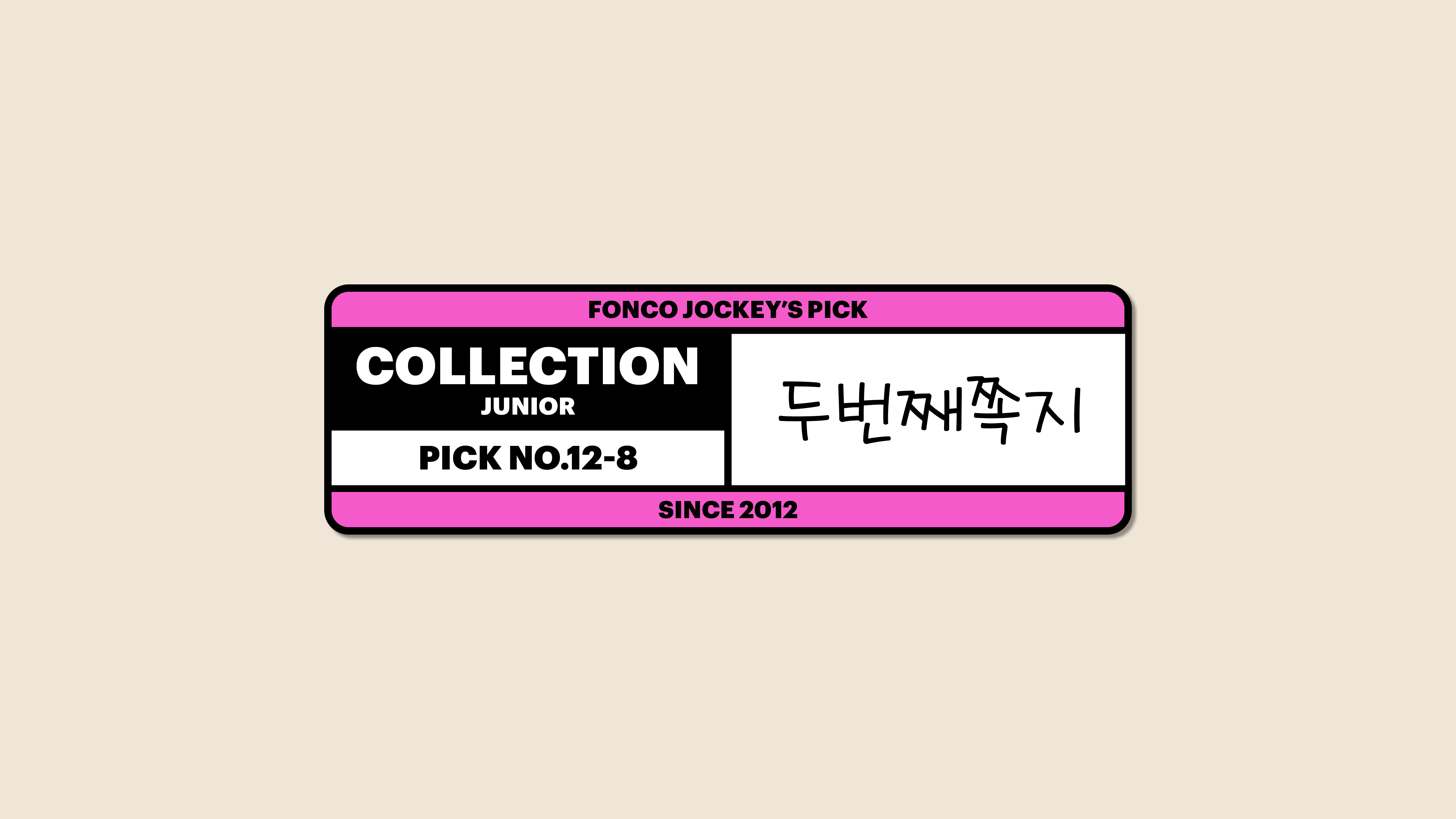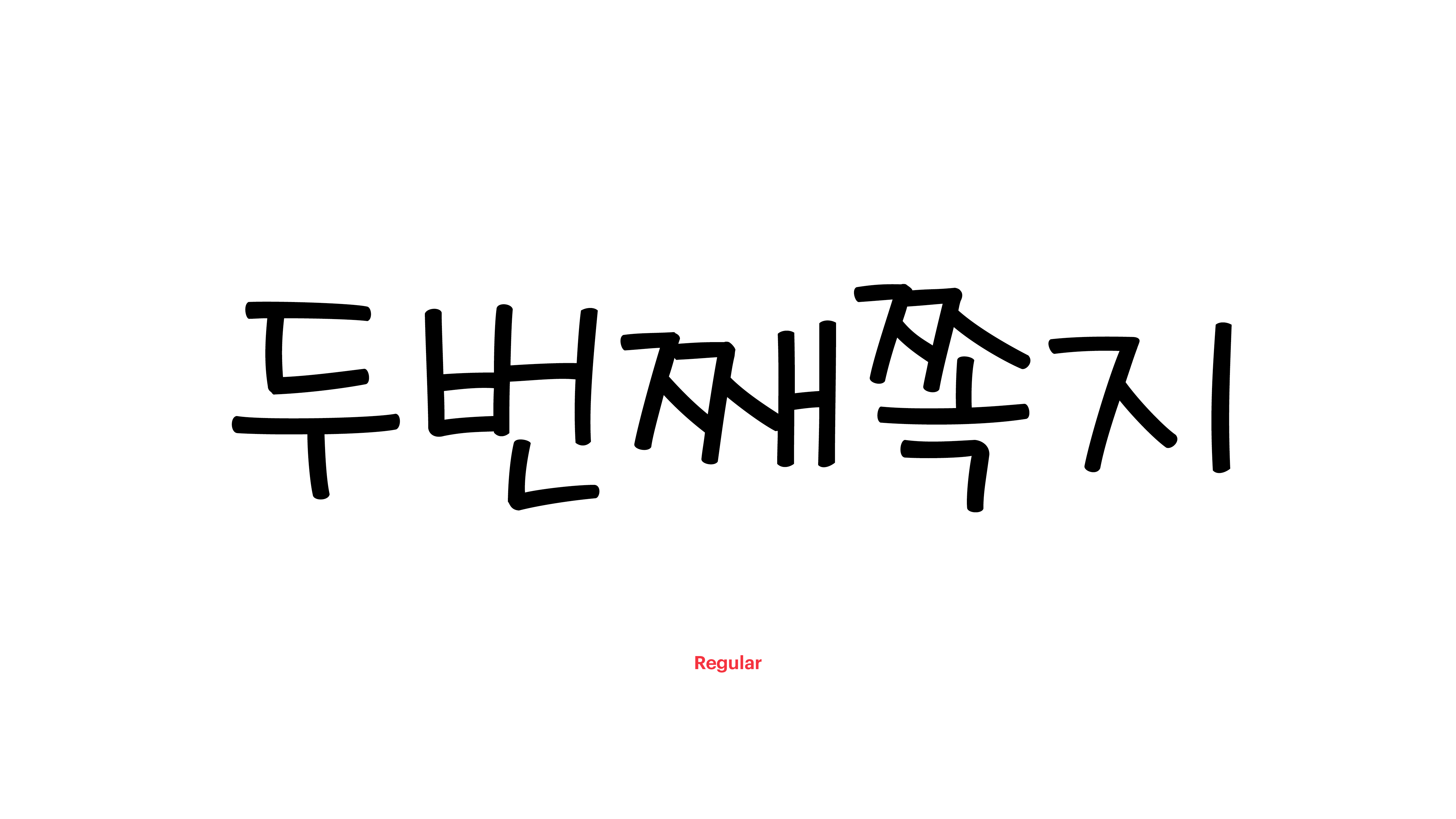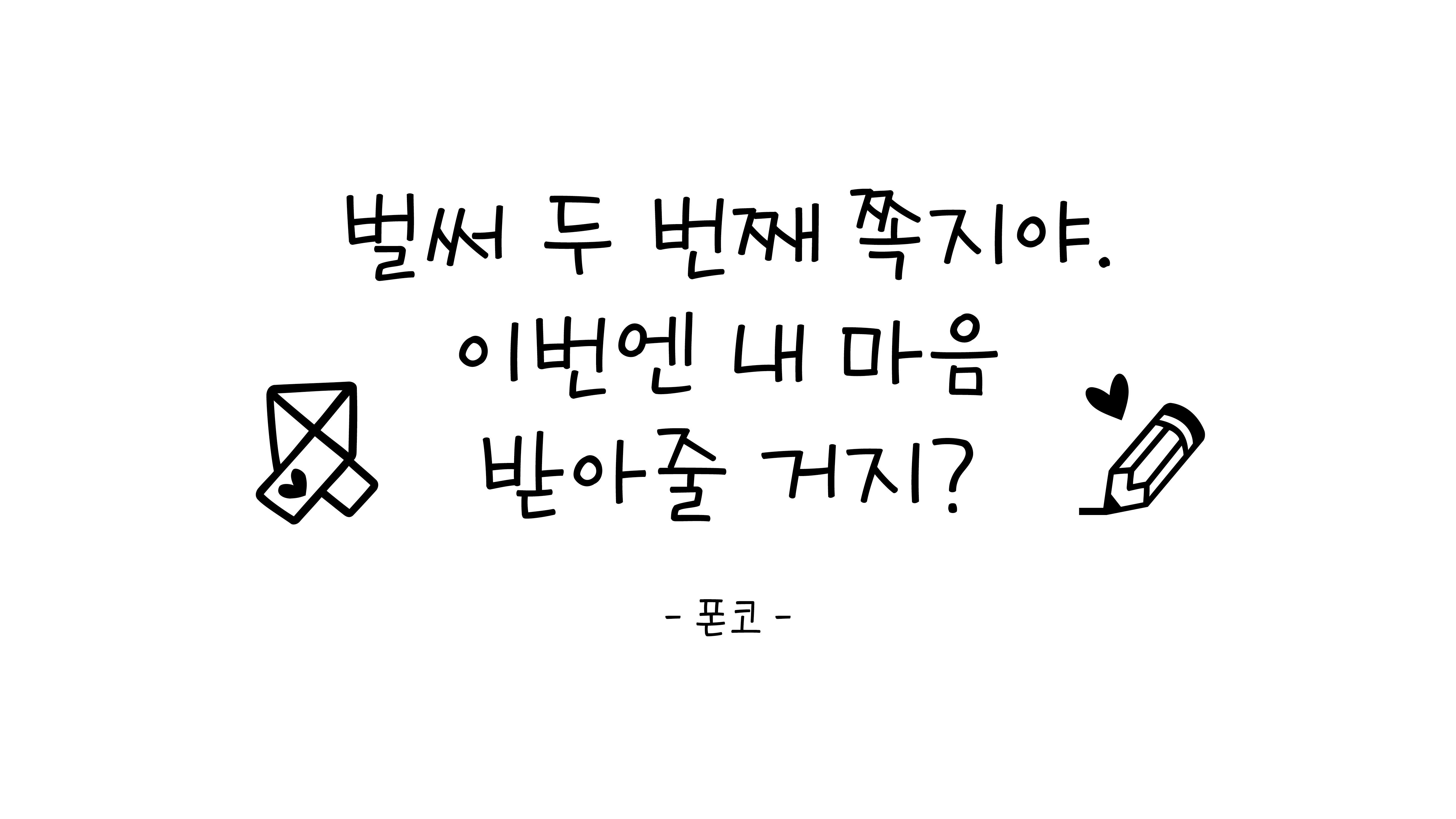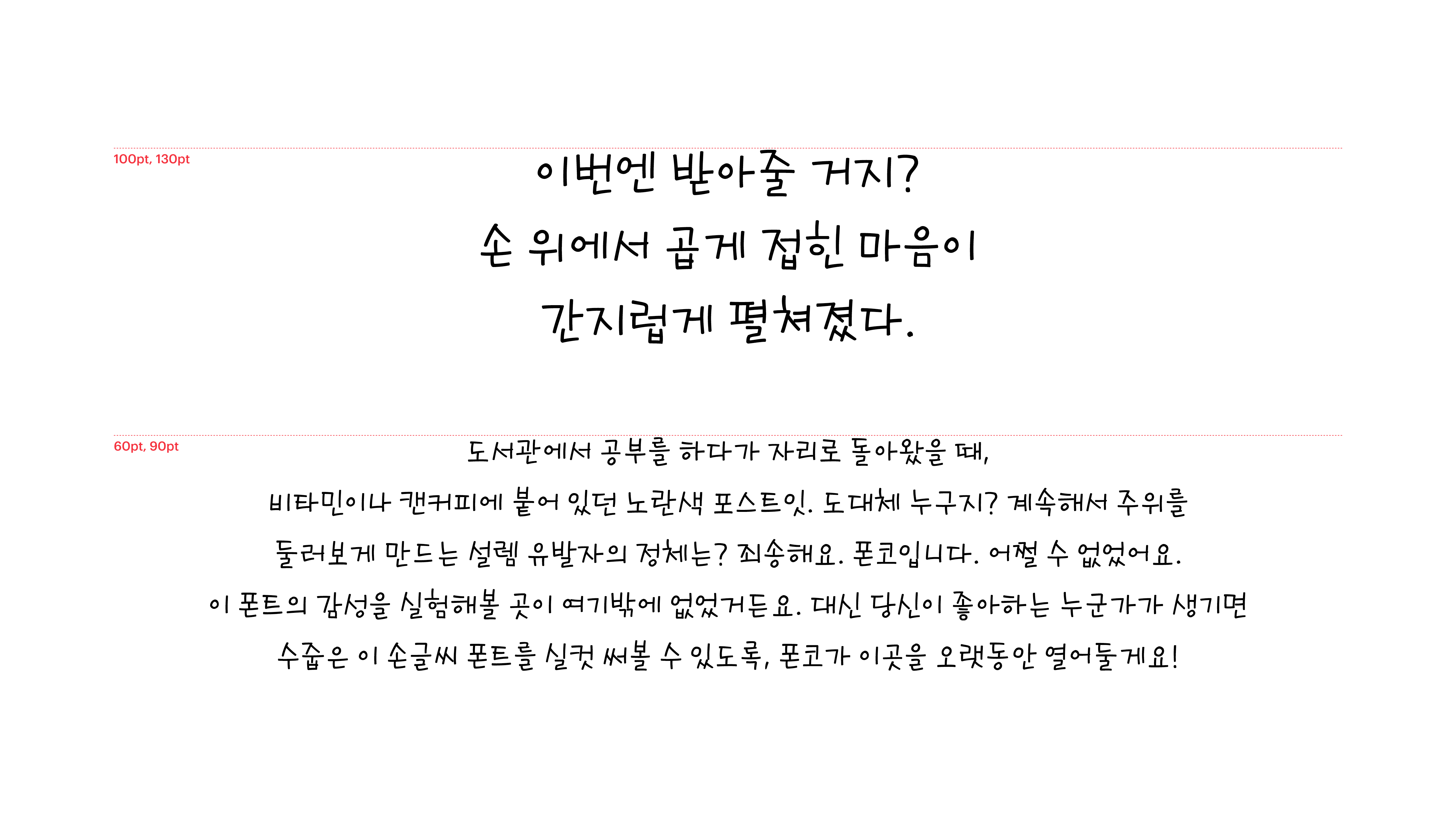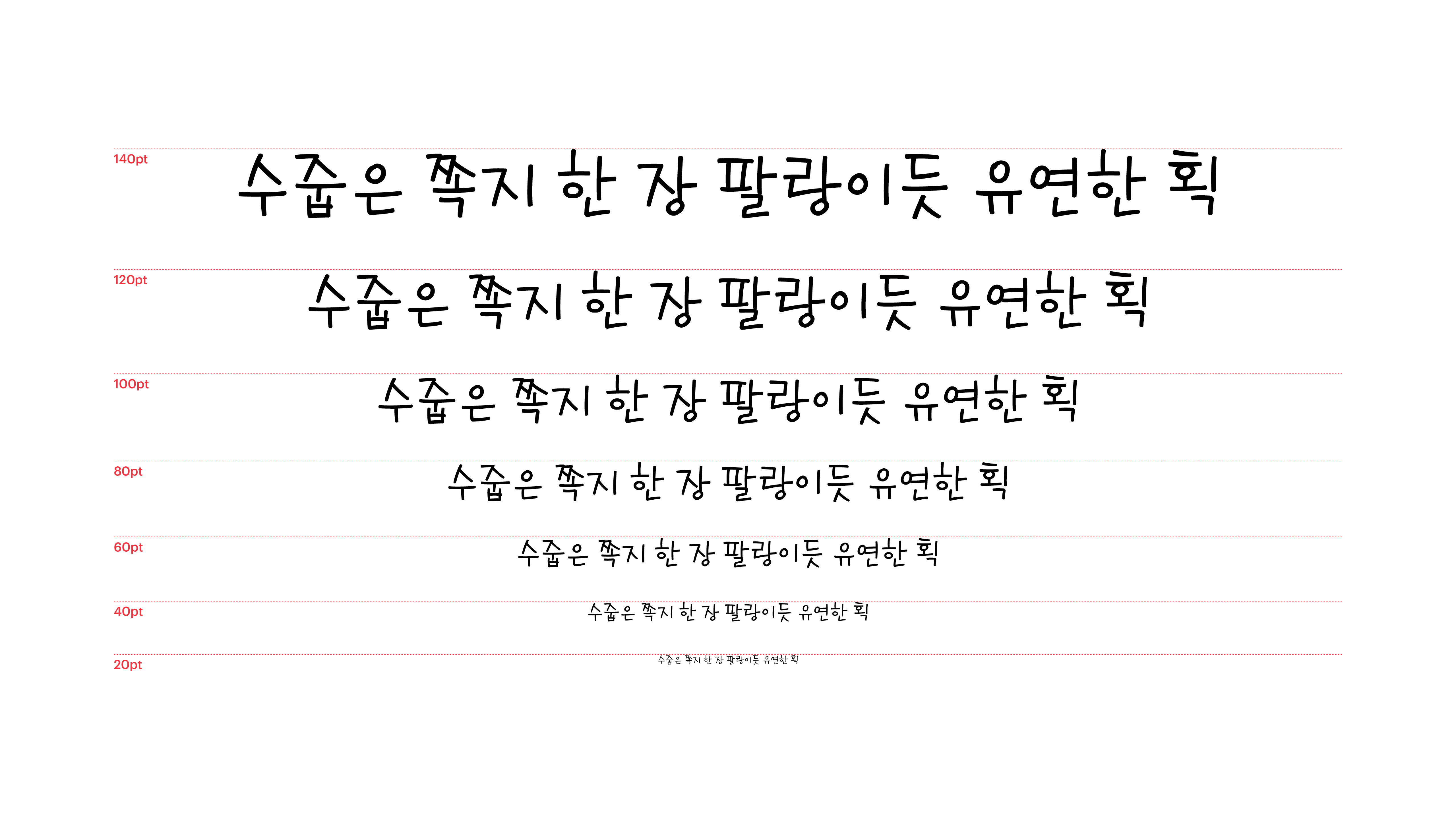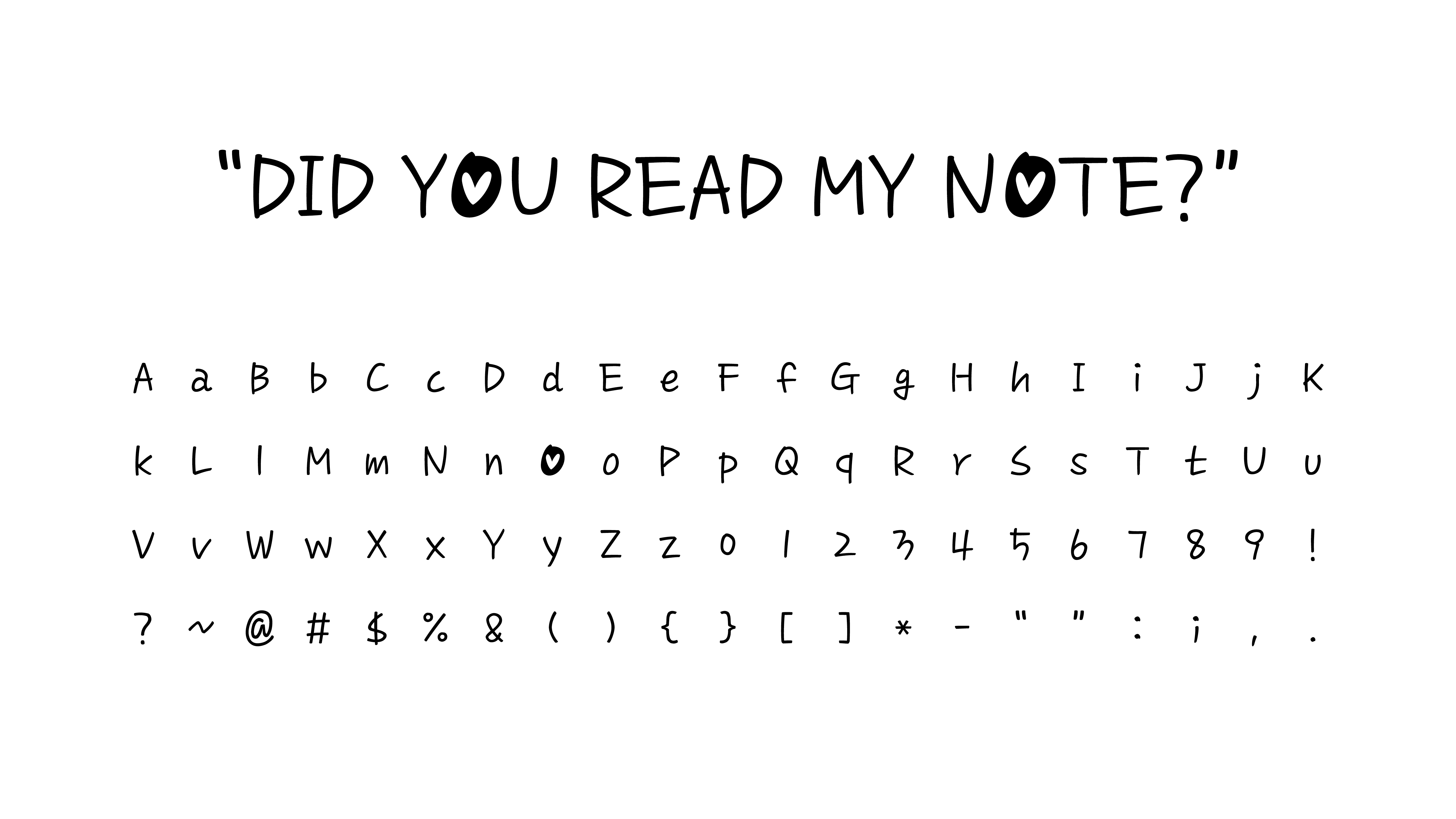
도서관에서 공부를 하다가 자리로 돌아왔을 때, 비타민이나 캔커피에 붙어 있던 노란색 포스트잇. 도대체 누구지? 계속해서 주위를 둘러보게 만드는 설렘 유발자의 정체는? 죄송해요. 폰코입니다. 어쩔 수 없었어요. 이 폰트의 감성을 실험해볼 곳이 여기 밖에 없었거든요. 대신 당신이 좋아하는 누군가가 생기면 수줍은 이 손글씨 폰트를 실컷 써볼 수 있도록, 폰코가 이곳을 오랫동안 열어둘게요!
Yoon 두번째쪽지